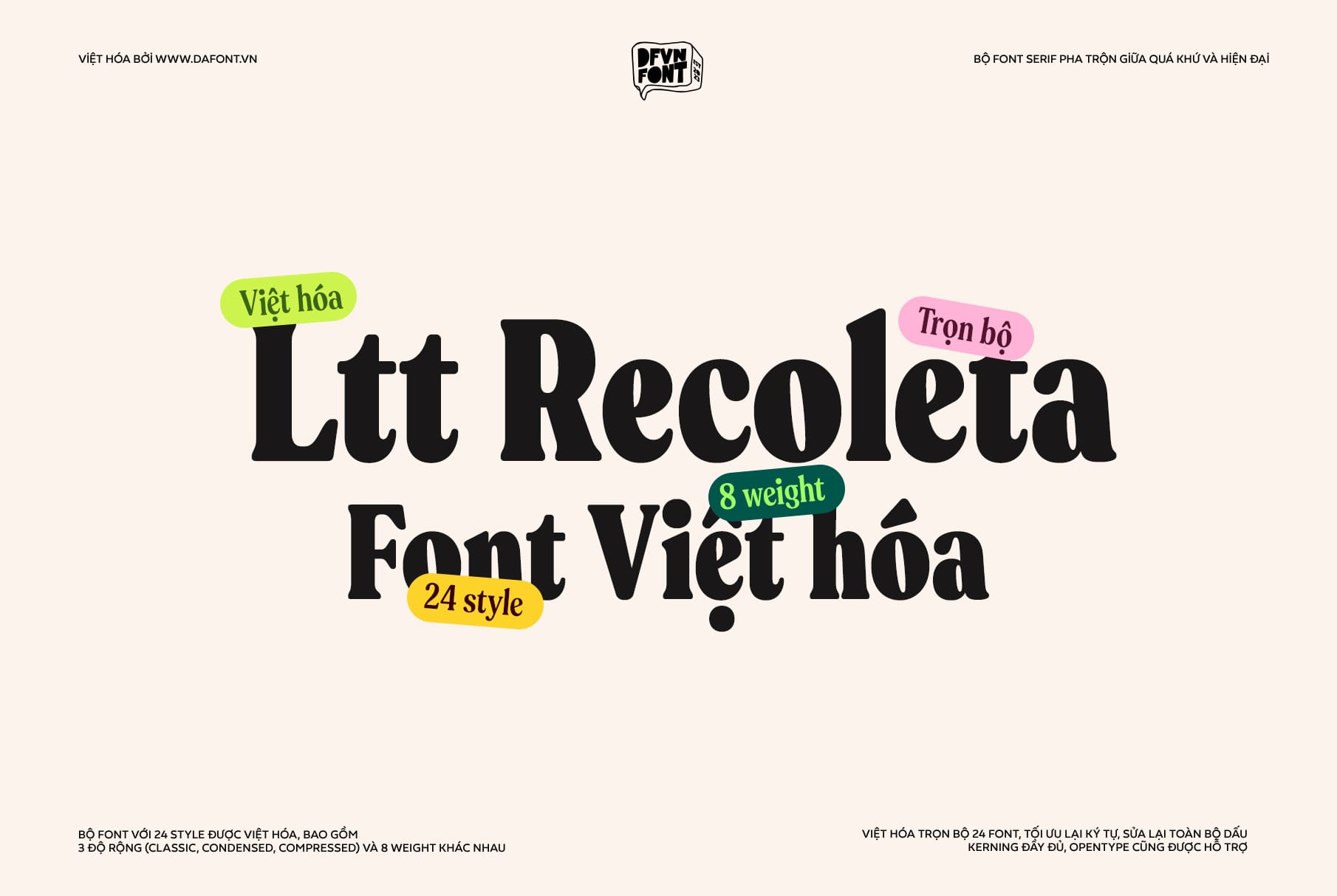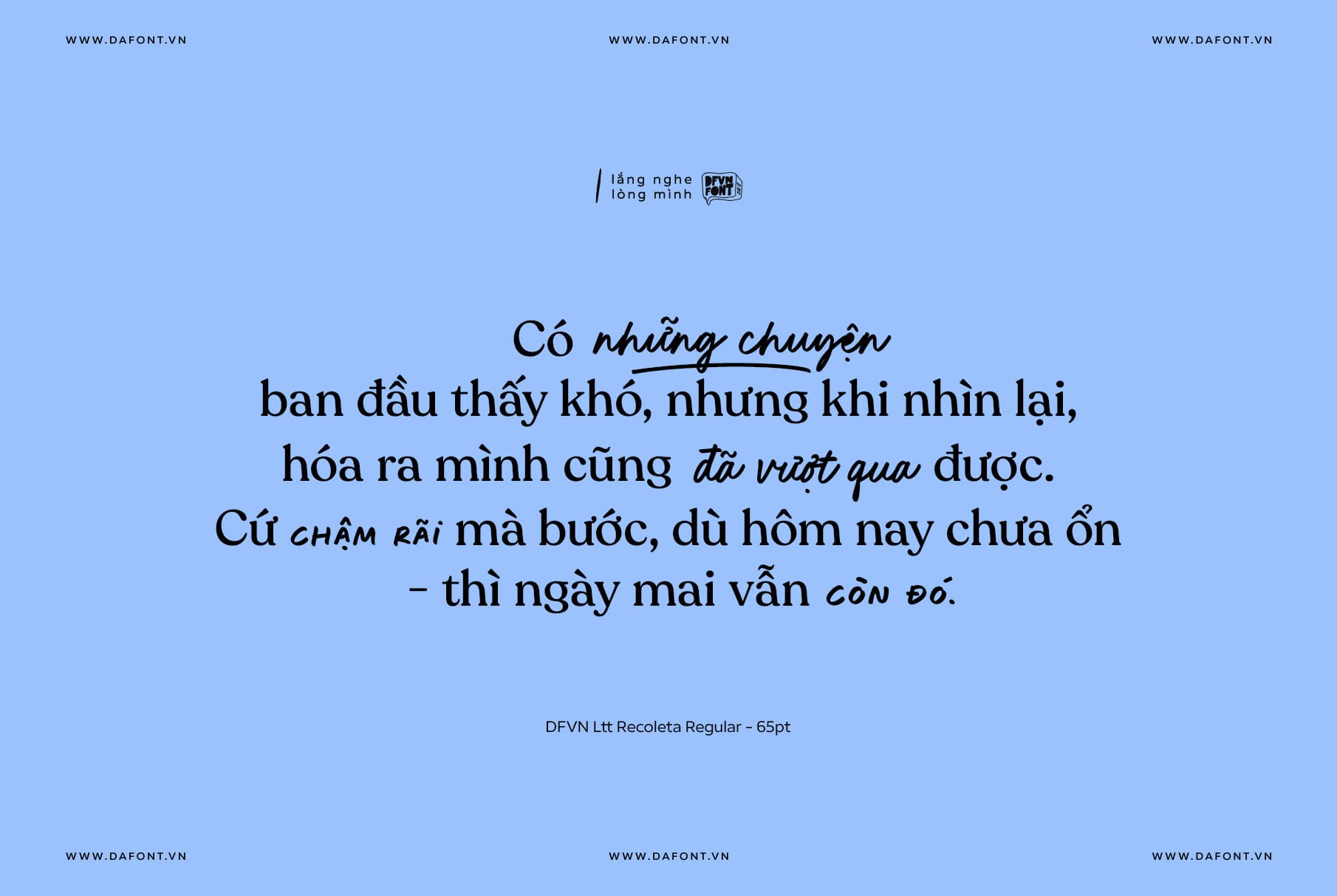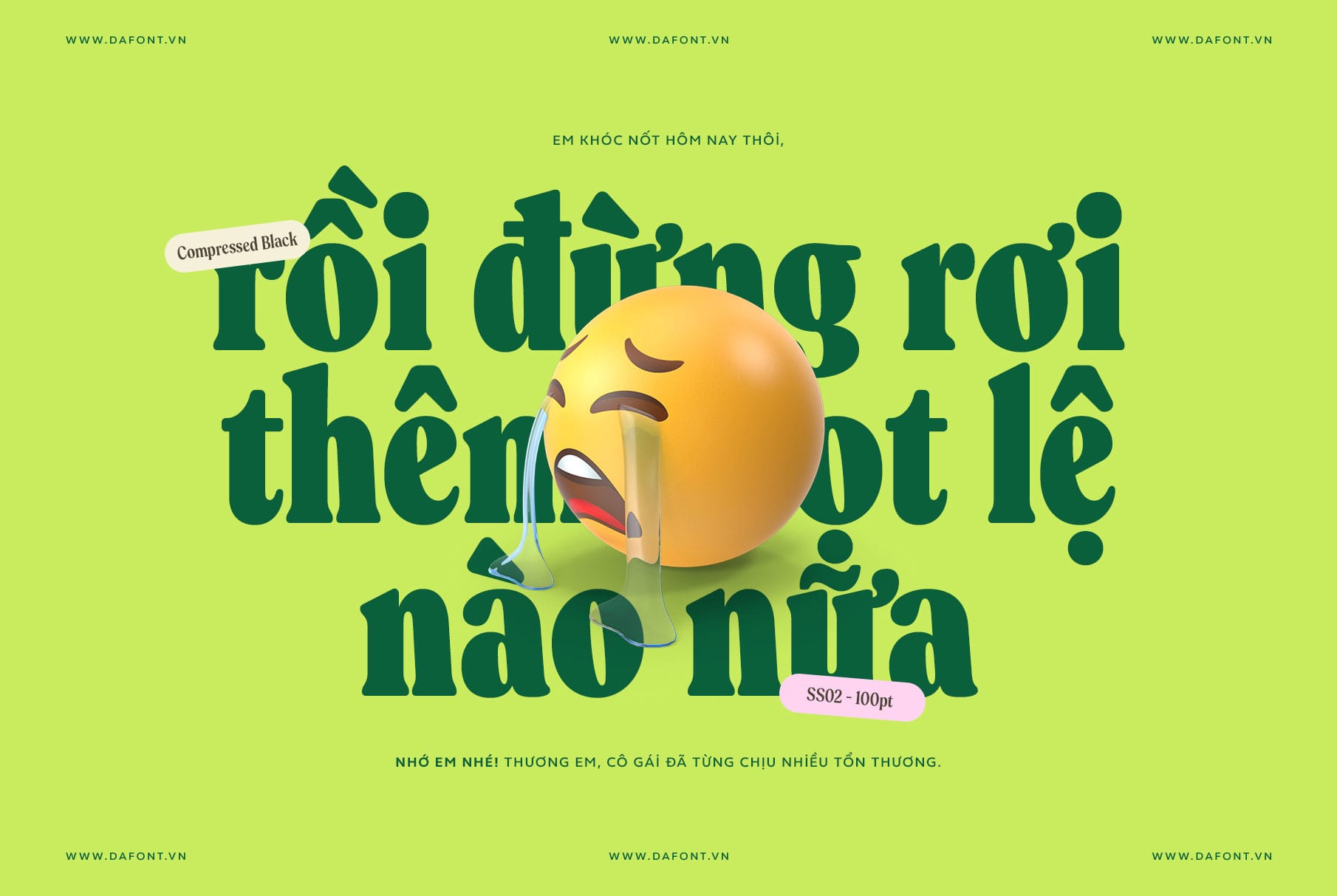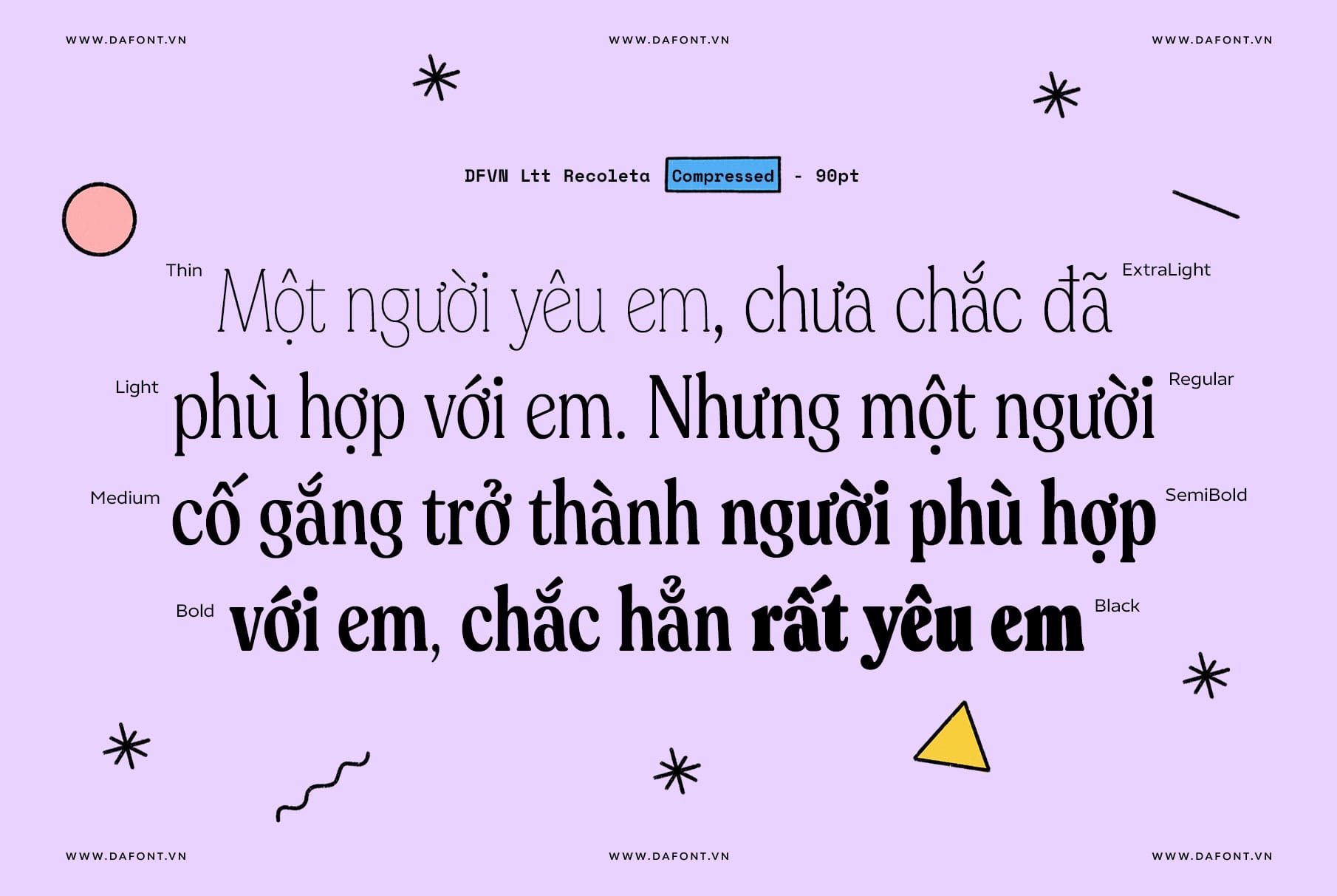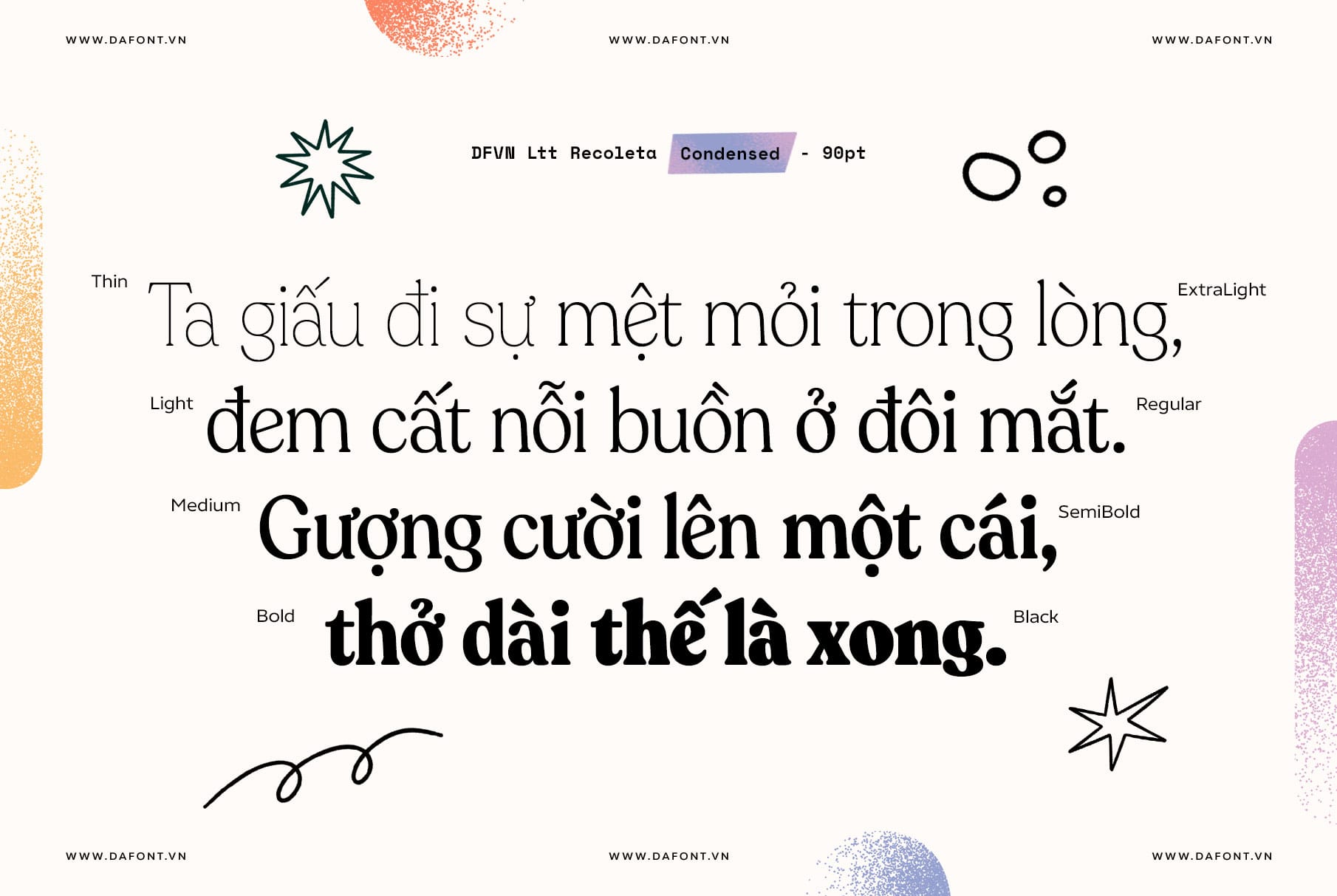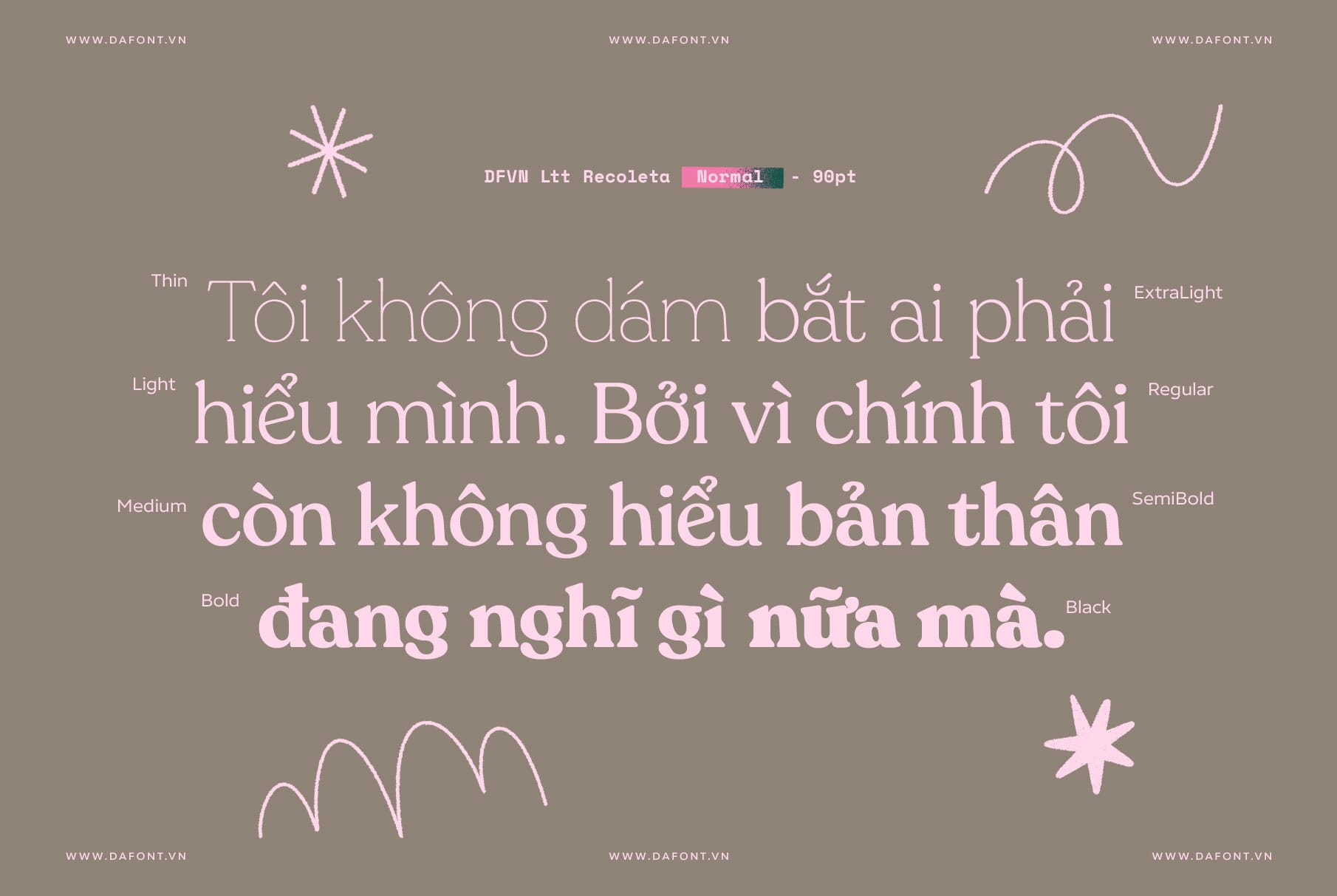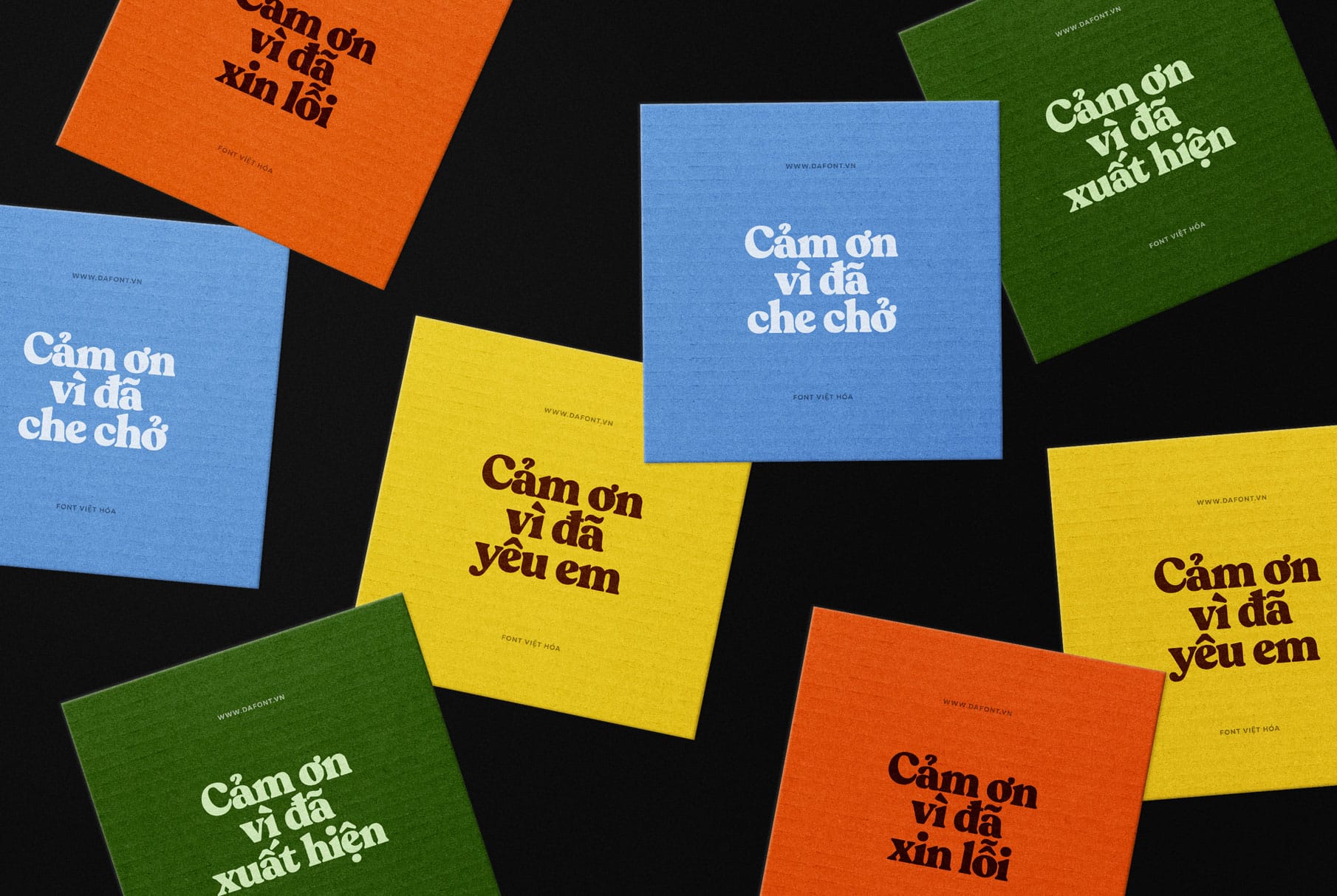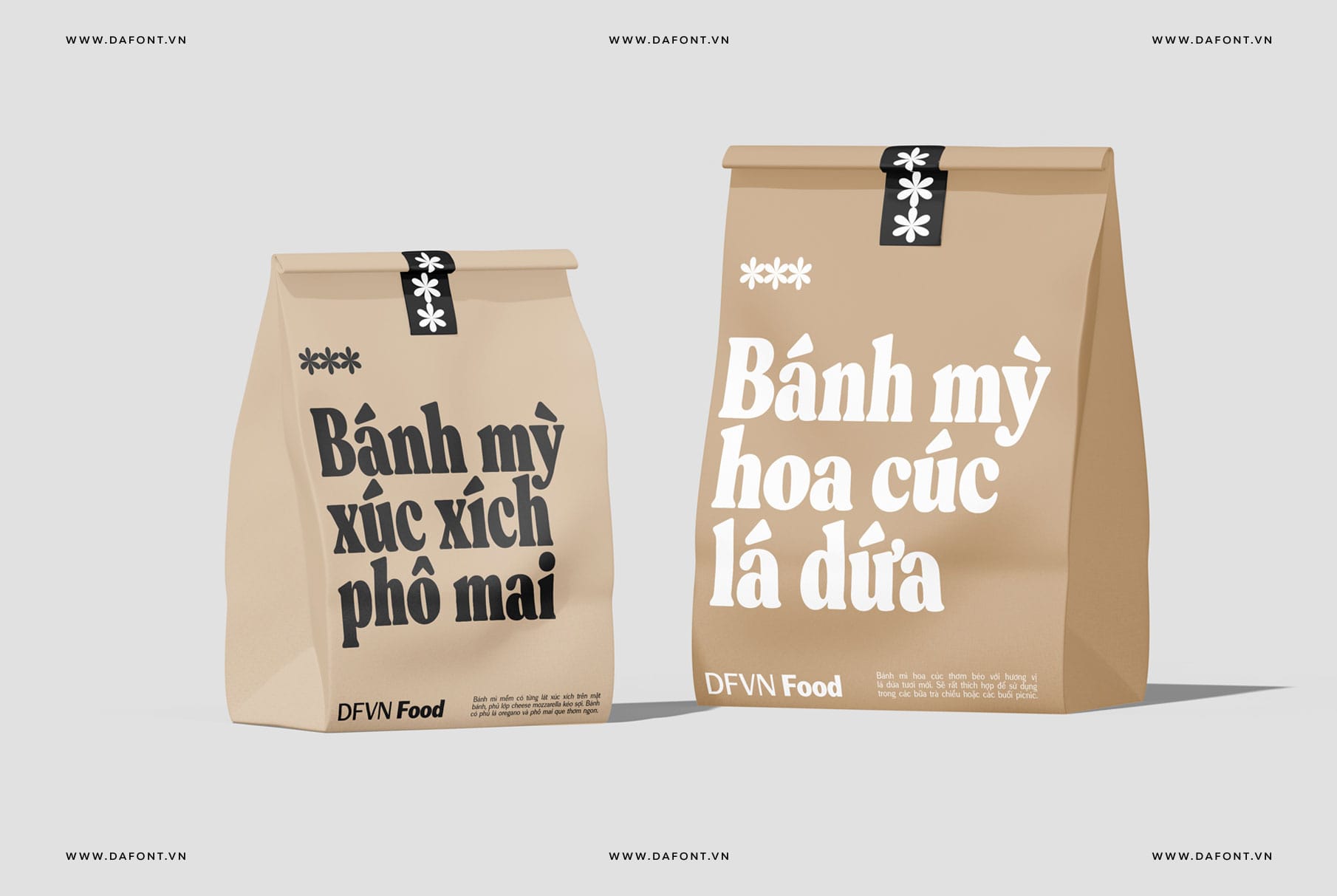
DFVN Ltt Recoleta (24 font)
Vẻ đẹp hoài cổ cho thiết kế hiện đại
DFVN LTT Recoleta font là một lựa chọn xuất sắc cho những ai đang tìm kiếm một font serif linh hoạt, kết hợp giữa vẻ đẹp cổ điển và sự hiện đại.
LTT Recoleta được ra mắt lần đầu vào năm 2018 và sau đó được mở rộng để đáp ứng nhu cầu ngày càng tăng của các nhà thiết kế. Font này lấy cảm hứng từ các font cổ điển như Windsor và Cooper, mang đậm phong cách của thập niên 1970 – 1980. Sự kết hợp giữa các đường cong mềm mại và nét hiện đại giúp LTT Recoleta trở nên độc đáo và dễ nhận biết.
Đặc điểm nổi bật của DFVN Ltt Recoleta
LTT Recoleta là một serif font mang vẻ đẹp hoài cổ kết hợp phong cách hiện đại, được ưa chuộng trong nhiều lĩnh vực thiết kế sáng tạo. Dưới đây là những đặc điểm nổi bật giúp font này trở nên đặc biệt:
• 24 phong cách: Bao gồm 3 độ rộng (Normal, Compressed, Condensed) và 8 độ đậm nhạt khác nhau (từ Thin đến Black).
• Sự pha trộn giữa cổ điển và hiện đại: Kế thừa tinh thần hoài cổ từ Cooper, kết hợp với cấu trúc gọn gàng để phù hợp xu hướng hiện đại.
• Kiểu chữ bo tròn mềm mại: Các đường nét cong uyển chuyển tạo cảm giác thân thiện và nghệ thuật.
• Tính năng bổ sung: Có nhiều lựa chọn chữ cái thay thế cho cả chữ hoa và chữ thường, giúp tùy chỉnh linh hoạt cho nhiều mục đích thiết kế.
DFVN LTT Recoleta phù hợp cho dự án thiết kế nào?
Là một serif display font mang tính thẩm mỹ cao, do đó nó thích hợp với những thiết kế cần sự nhấn mạnh thị giác, nhất là trong các lĩnh vực sáng tạo hoặc thương hiệu có phong cách.
• Logo và nhận diện thương hiệu cao cấp: Recoleta mang phong cách cổ điển và sang trọng, giúc logo trở nên đồng nhất và gây ấn tượng.
• Poster, quảng cáo, tiêu đề nổi bật: Các thiết kế in ấn cần điểm nhấn trực quan sẽ được nâng tầm với Recoleta.
• Editorial design (tạp chí, bìa sách, trích dẫn): Recoleta giúp làm nổi bật tiêu đề hoặc đoạn trích đặc biệt.
• Bao bì sản phẩm: Rất phù hợp cho mỹ phẩm, thời trang, thực phẩm, đồ ăn uống nhờ cảm giác thủ công và tinh tế.
• Website landing page: Dùng làm tiêu đề hoặc call-to-action để tạo ấn tượng ban đầu mạnh mẽ.
• Thiết kế mạng xã hội: Các bài đăng thương hiệu mang thông điệp rõ ràng và sang trọng.
DFVN LTT Recoleta có phù hợp với văn bản dài không?
Recoleta không phải là font lý tưởng cho body text dài và nhỏ, do đặc trưng trình bày dành cho display. Tuy nhiên, khi đặt đúng ngữ cảnh (như tiêu đề hoặc trích dẫn), font sẽ phát huy tính thẩm mỹ vượt trội. Bạn cũng có thể kết hợp với các font chữ sans serif hoặc script để tạo ra những điểm nhấn ấn tượng khi sử dụng Recoleta.
Kết luận
DFVN LTT Recoleta là một font serif đa năng với 24 phong cách, hỗ trợ đa ngôn ngữ. Với phong cách vừa cổ điển, vừa mới mẻ, Recoleta hoàn hảo cho những nhãn hàng muốn tạo sự khác biệt trong thiết kế.
Bộ font được Việt hóa một cách chỉn chu, với toàn bộ ký tự và dấu tiếng Việt được tinh chỉnh cẩn thận, khoảng cách chữ (kerning) được tối ưu hóa. Ngoài ra, nhiều ký tự thay thế cũng đã được Việt hóa và có thể dễ dàng kích hoạt thông qua tính năng Opentype.